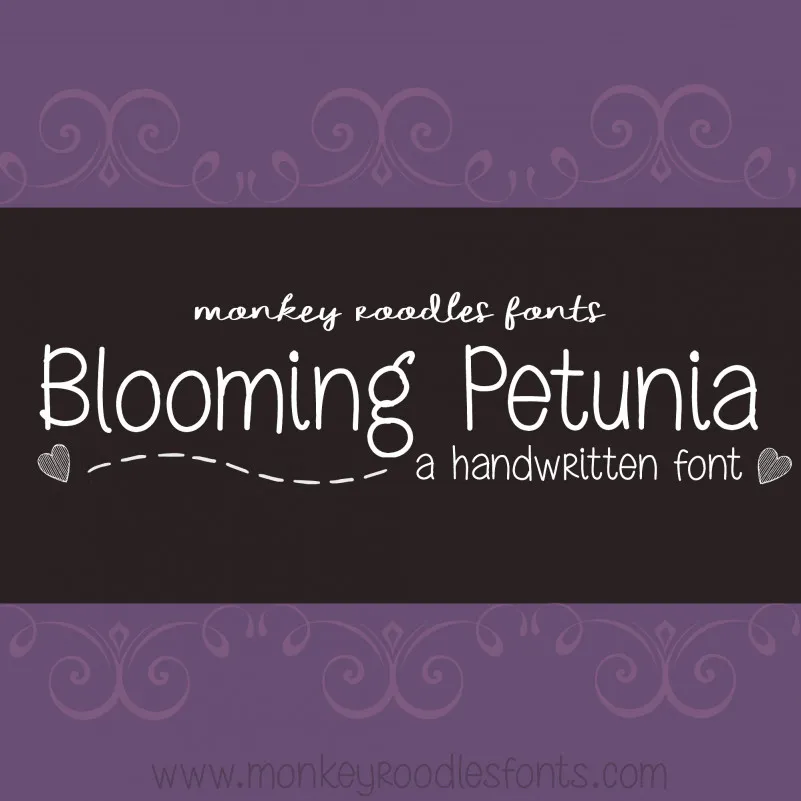
MRF Blooming Petunia Font – Download Grátis
Descubra a delicadeza e a tranquilidade da MRF Blooming Petunia Font ao encontrar uma fonte que combina características elegantes com um toque naturalmente descontraído. Desenvolvida pelo designer Hamilton, esta fonte é perfeita para quem busca uma mistura única de grãos manuais e linhas suaves. Perfeito para designers gráficos, desenvolvedores de sites ou qualquer profissional que aprecia a beleza do texto sem ser desafiado pela rigidez da tipografia tradicional, esta fonte oferece um equilíbrio perfeito entre personalidade e legibilidade. Ideal tanto para uso pessoal quanto para projetos comerciais, mas lembre-se de comprar uma licença se desejar incorporá-la em trabalhos profissionais. A MRF Blooming Petunia é mais do que simplesmente uma fonte de texto; ela captura a essência da natureza em sua forma mais delicada. Adicione esta fonte à sua biblioteca e veja como ela pode transformar seu design, seja em cartões de aniversário personalizados ou sites responsivos. Descubra o encanto de uma fonte que combina a elegância do handwritten com a vivacidade de uma flor de petunia em cada linha. A MRF Blooming Petunia Font é mais do que uma escolha gráfica, ela é um convite para explorar os limites do design e revelar o seu próprio toque único.